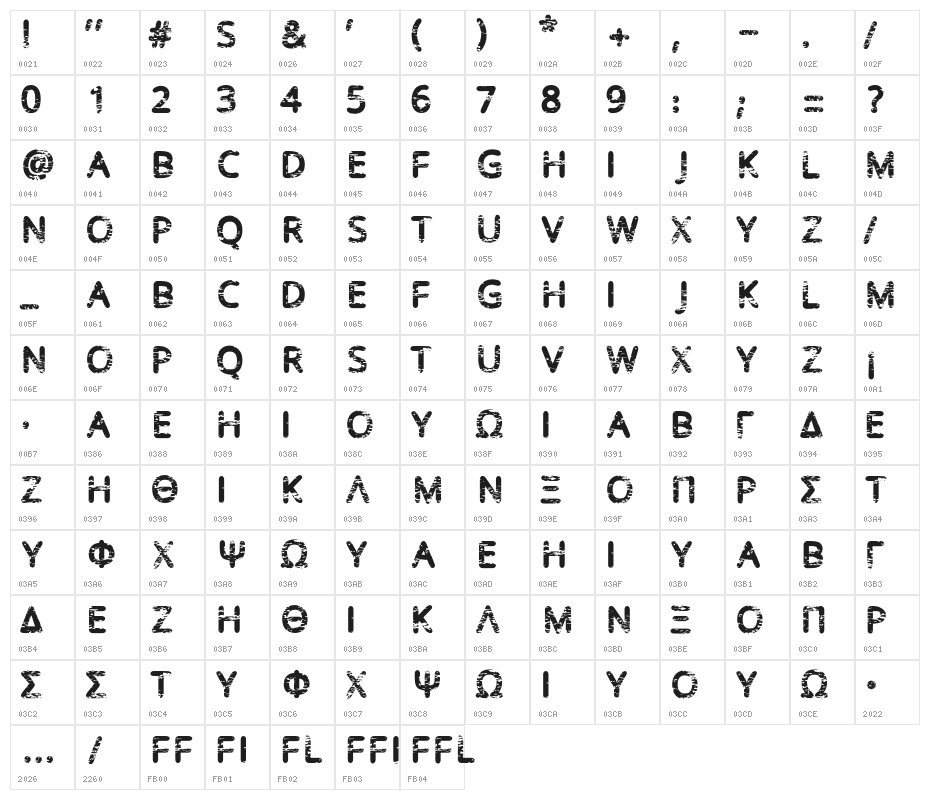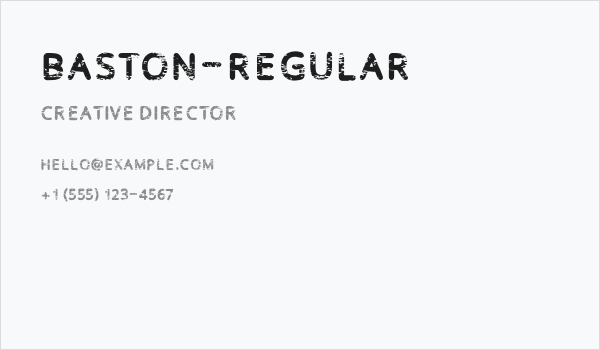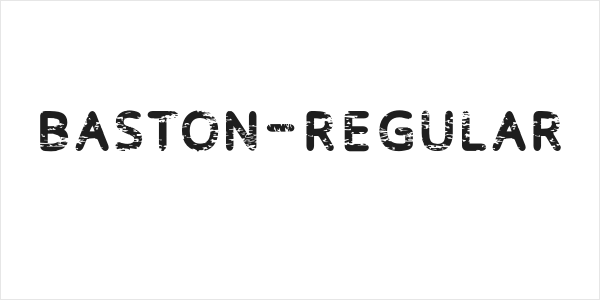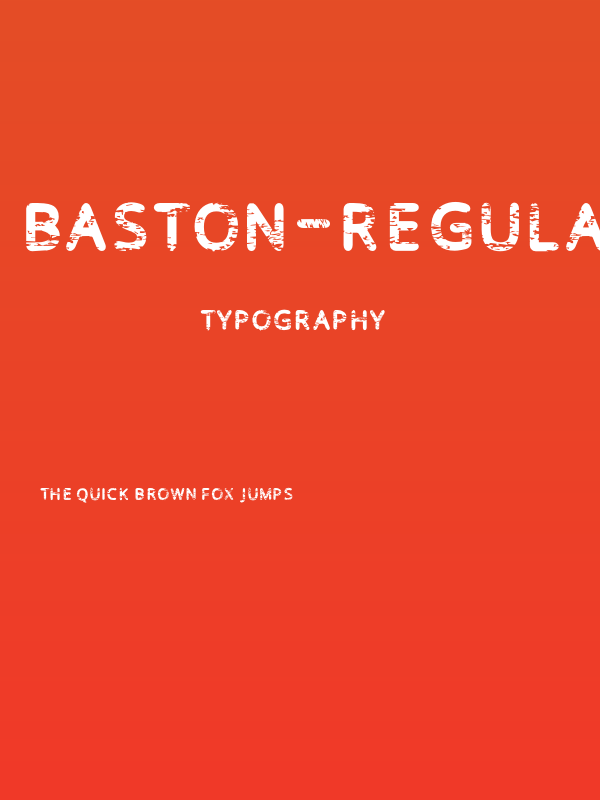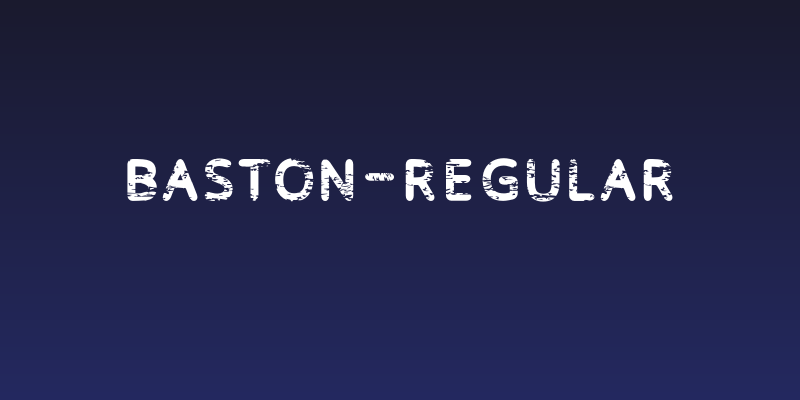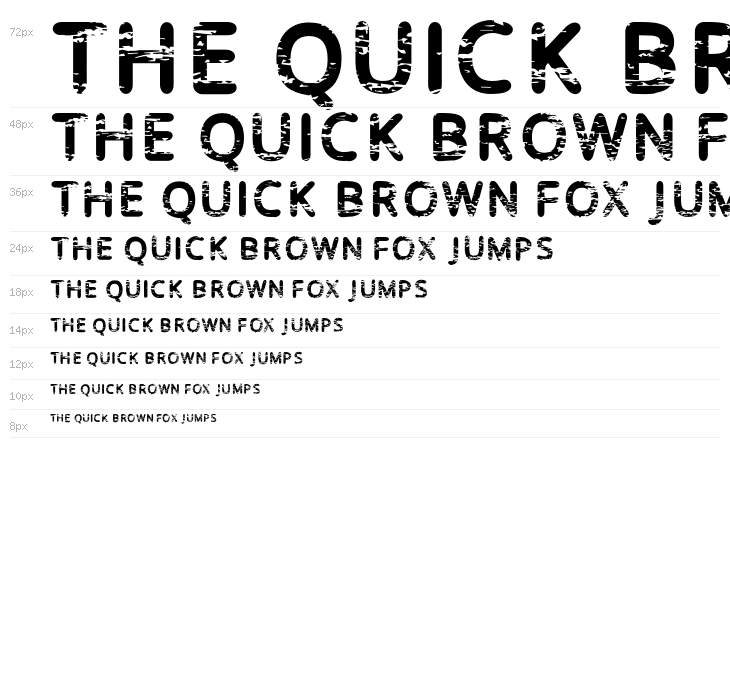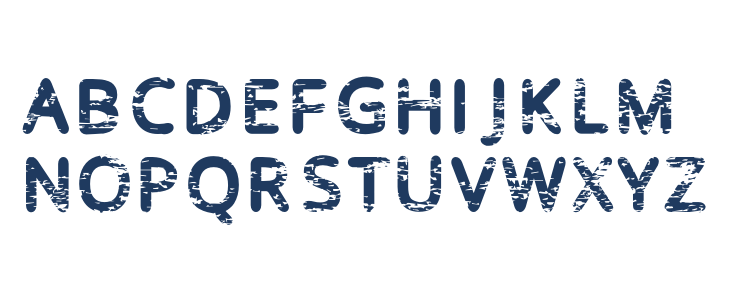
Baston-Regular Font
✎ Distorted Eroded
| Progetti proposti | Ideal for poster designs, album covers, branding for edgy or alternative products, and any project needing a vintage or rugged aesthetic. |